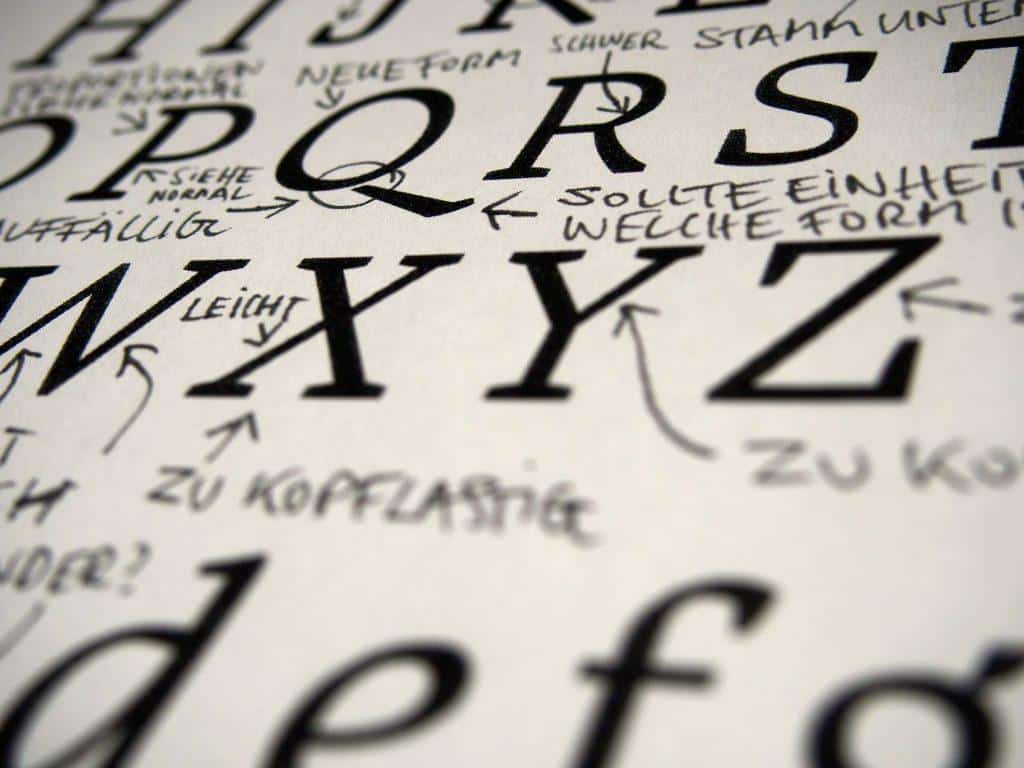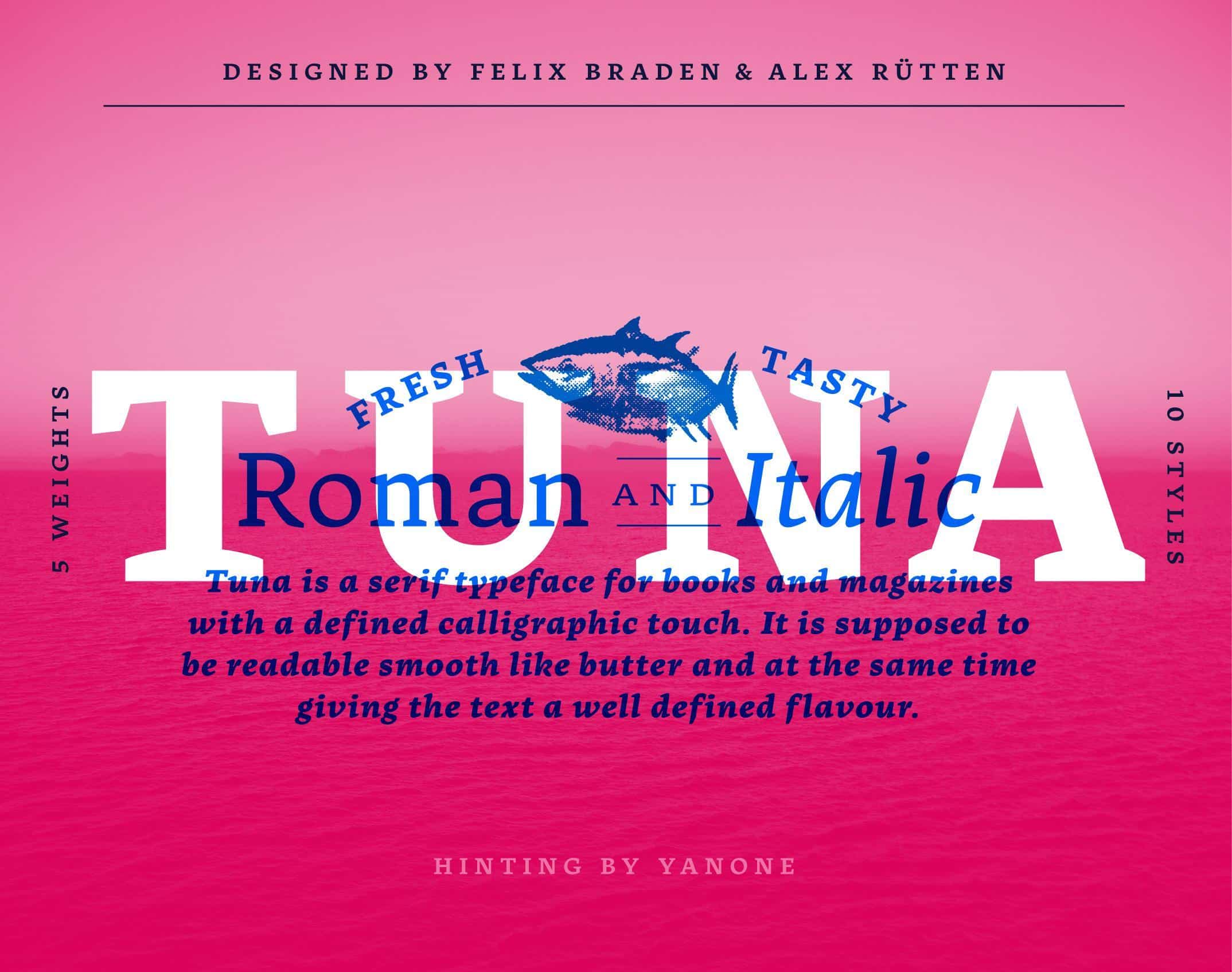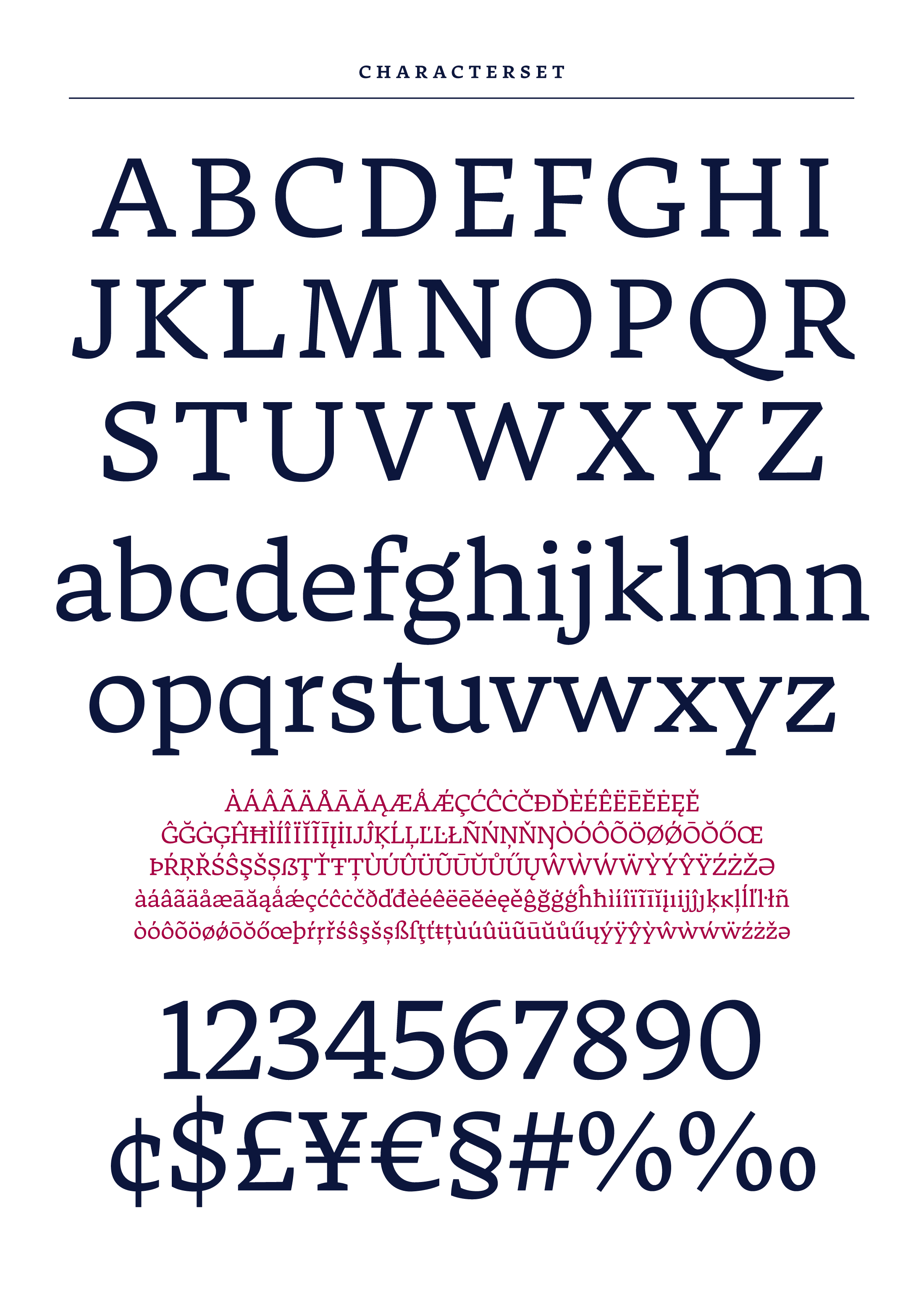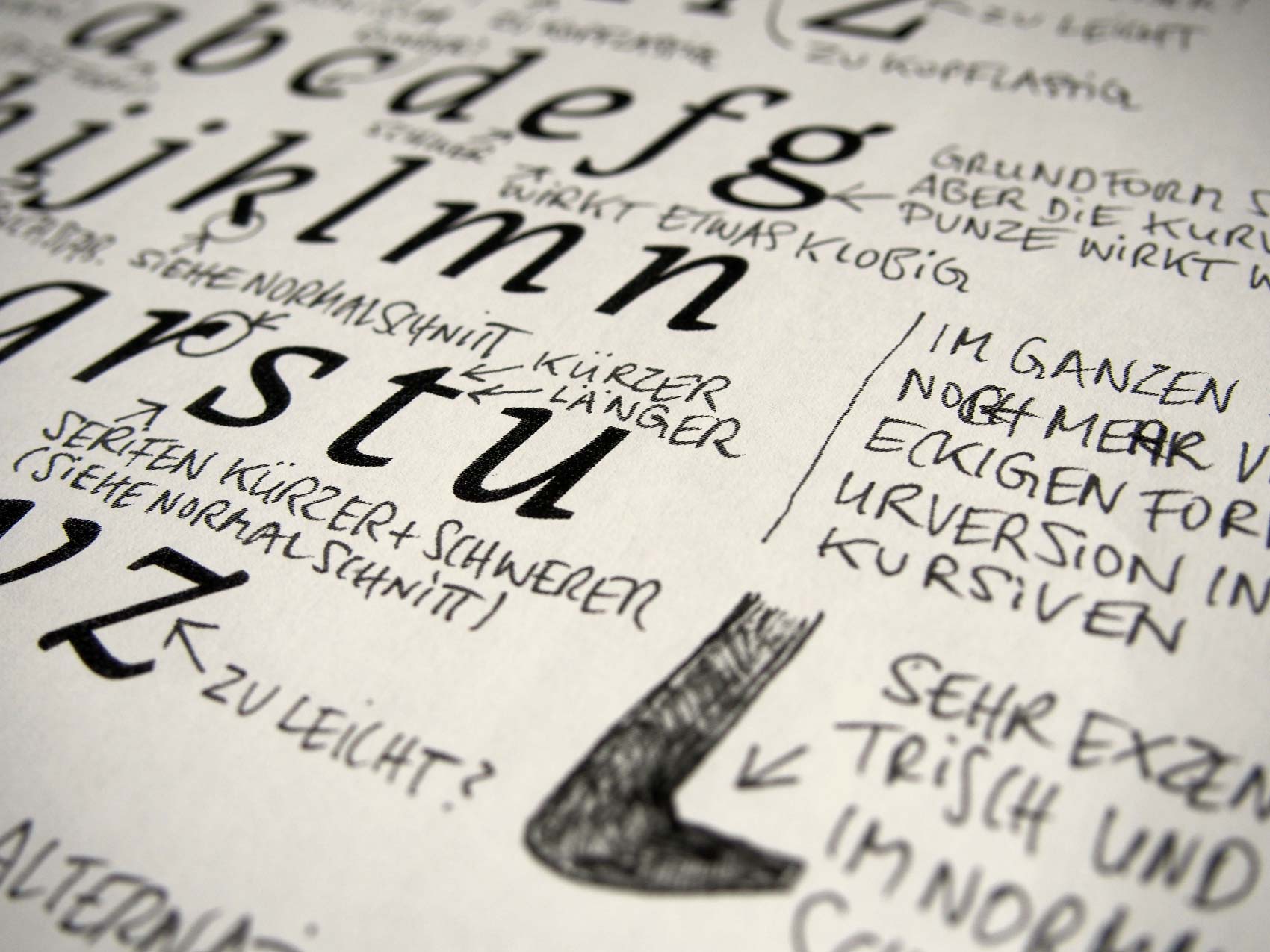
TUNA ist ein Allround -Typeface für Print und Screen der Typografen Felix Braden und Alex Rütten aus Köln bzw. Berlin. Beide kannten sich zunächst nur vom Sehen – noch aus dem Studientagen – beide hatten an derselben Fachhochschule in Trier studiert und sind sich dann zufällig auf dem Design-Mai in Berlin über den Weg gelaufen. Da sie stellten fest, dass sie sich beide für Schriften und Schriftgestaltung interessieren. Seitdem haben sich beide oft über ihre neuesten Designs und über Schriften allgemein ausgetauscht.
Tuna macht in allen Schnitten einen rundum gelungenen Eindruck. Der Lesefluss wird deutlich unterstützt, es holpert nichts und es tanzt praktisch keiner aus der Reihe. Dennoch vermittelt Tuna eine höchst vitale, ‚jazzy‘ Note.
Alex: Vielen Dank für das Kompliment! Das ist ein Punkt uns an dem Design auch gefällt. Tatsächlich ’swingt‘ die Schrift, funktioniert aber trotzdem sehr gut im Lesefluss.
Felix: Ich denke, das hat mit der Individualität der einzelnen Zeichen zu tun. Das fördert nicht nur die Lesbarkeit sondern gibt der Schrift auch einen deutlichen Charakter – wenn man das zu einem harmonischen Ganzen verbinden kann.
Ich stelle mir eine Zusammenarbeit an einem Font sehr kompliziert vor. Wo liegen Eure verschiedenen Talente? Gab es eine Arbeitsteilung?
Alex: Ich würde sagen, dass unsere Talente relativ ähnlich waren. Wir hatten beide schon Schriften gestaltet und herausgebracht. Der jeweilige Fokus vom Designansatz her war indes verschieden: Felix hat eher ein Faible für geometrische Schriften, während mich vor allem Antiquas interessieren. An den jeweiligen Arbeitsschritten haben wir aber zu gleichen Teilen gearbeitet. Bei der Vermarktung haben wir dann die Aufgaben geteilt: Felix hat sich um die Öffentlichkeitsarbeit gekümmert und ich habe die Programmierung der Schriftmuster-Webseite übernommen.
Wie diskutiert man per Skype über zwei Jahre eine Font-Entwicklung? Wie lief der visuelle Part der Diskussionen?
Alex: Der größte Teil des Austauschs zu Designfragen lief tatsächlich über Emails, wo wir uns den jeweils aktuellen Stand der Änderungen hin und her geschickt haben. Mindestens einmal im Jahr haben wir uns dann natürlich auf der Typo in Berlin getroffen und sind wir dann immer einen Haufen Ausdrucke zusammen durchgegangen.
Auf Eurer Microsite zeigt Ihr unter http://tuna-typeface.com/#process allererste Skizzen der Tuna. Welche Gedanken hatten Euch damals geleitet/ bzw. Eure Hände geführt? Auf welchen Bedarf bzw. Mangel habt Ihr mit Tuna reagiert?
Felix: Die Grundidee ist, eine richtig gut lesbare Serifen-Schrift für den Bildschirm und für Print zu entwickeln – einen cross-medialen Allrounder. Alex hatte vor ein paar Jahren einen Vortrag über Bildschirmoptimierung in Köln gehalten. Ich hatte mir daraufhin vorgenommen, das geballte Wissen in eine Schrift zu packen. Das Ergebnis in kleinen Schriftgraden war total überzeugend und am Bildschirm extrem gut lesbar. Leider wirkte es in besserer Auflösung sehr kühl, fast seelenlos.
Alex: Als Felix mir vor mittlerweile einigen Jahren doch ziemlich unzufrieden seinen neusten Schriftentwurf zeigte, war das Design tatsächlich steril und sehr generisch; dem Schriftbild fehlte es an Charme. Mein Eindruck war aber, dass Potential vorhanden war, um daraus etwas zu machen. Also habe ich ihm gesagt, dass ich mal versuchen würde, dem ganzen eine andere Richtung zu geben – mehr Individualität in den einzelnen Buchstaben, mehr Eigenheiten in den Details, so in diese Richtung. Als ich ihm dann die Überarbeitung zeigte, war er sehr zufrieden mit dem Ergebnis und wir beschlossen, zusammen weiter daran zu arbeiten.
Wenn man sich die Korrekturbögen ansieht, dann wird klar, dass Typografie eine Sisyphusarbeit sein muss. Warum tut sich das einer an?
Alex: Das ist eine gute Frage! Die sich aber bei vielen Disziplinen stellen lässt. Ein Pianist muss ja beispielsweise auch sehr viel Zeit investieren bis er auf einem Niveau spielt, mit dem er auch erfolgreich ist – ohne tägliches Training geht da nichts. So ähnlich sehe ich das auch bei der Schriftgestaltung – der Weg ist das eigentliche Ziel und die fertigen Schriften immer nur Etappen auf dem Weg.
Felix: Neben der ganzen Quälerei gibt es auch viele Pluspunkte wie z.B. eine jahrhundertelange Tradition, ganz viel spannende Forschung und Wissen, die Arbeit mit der reinen Form, ein guter Zweck, eine tolle Community… und wenn man mal begonnen hat, sich mit dem Thema zu beschäftigen ist es wie ein Virus. Schrift ist überall und man findet ständig etwas zum analysieren.
Ihr betont den ‚Handwriting‘-Aspekt bei der Entstehung der Tuna. Wie habt ihr die Kurve von der mittelalterlichen Handschrift via den Marker zur fertigen Tuna gekriegt?
Felix: Der Weg ist nicht so weit, wie man denkt, denn in der Grundform lesen wir heute immer noch hauptsächlich Renaissance-Schriften – zumindest, was die Buch-Typografie angeht. Daraus digitale Kurven zu machen, erfordert zwar ein gewisses Fingerspitzengefühl, ist aber kein Hexenwerk. In vielen Formen ist Tuna allerdings auch sehr vorwärtsgewandt und unterscheidet sich deutlich von den historischen Vorbildern. Ich denke, es hat sehr geholfen, nicht zu konsequent an bestehenden Konzepten festzuhalten. Das kleine a ist dafür ein gutes Beispiel: Es ist nach historischen Vorbildern zu geschlossen und zu breit – für eine gute Lesbarkeit am Bildschirm war es aber nötig, die Form zu verändern – also haben wir das einfach gemacht.